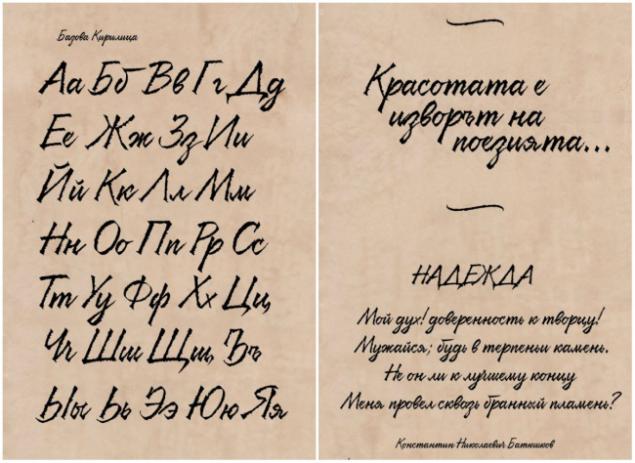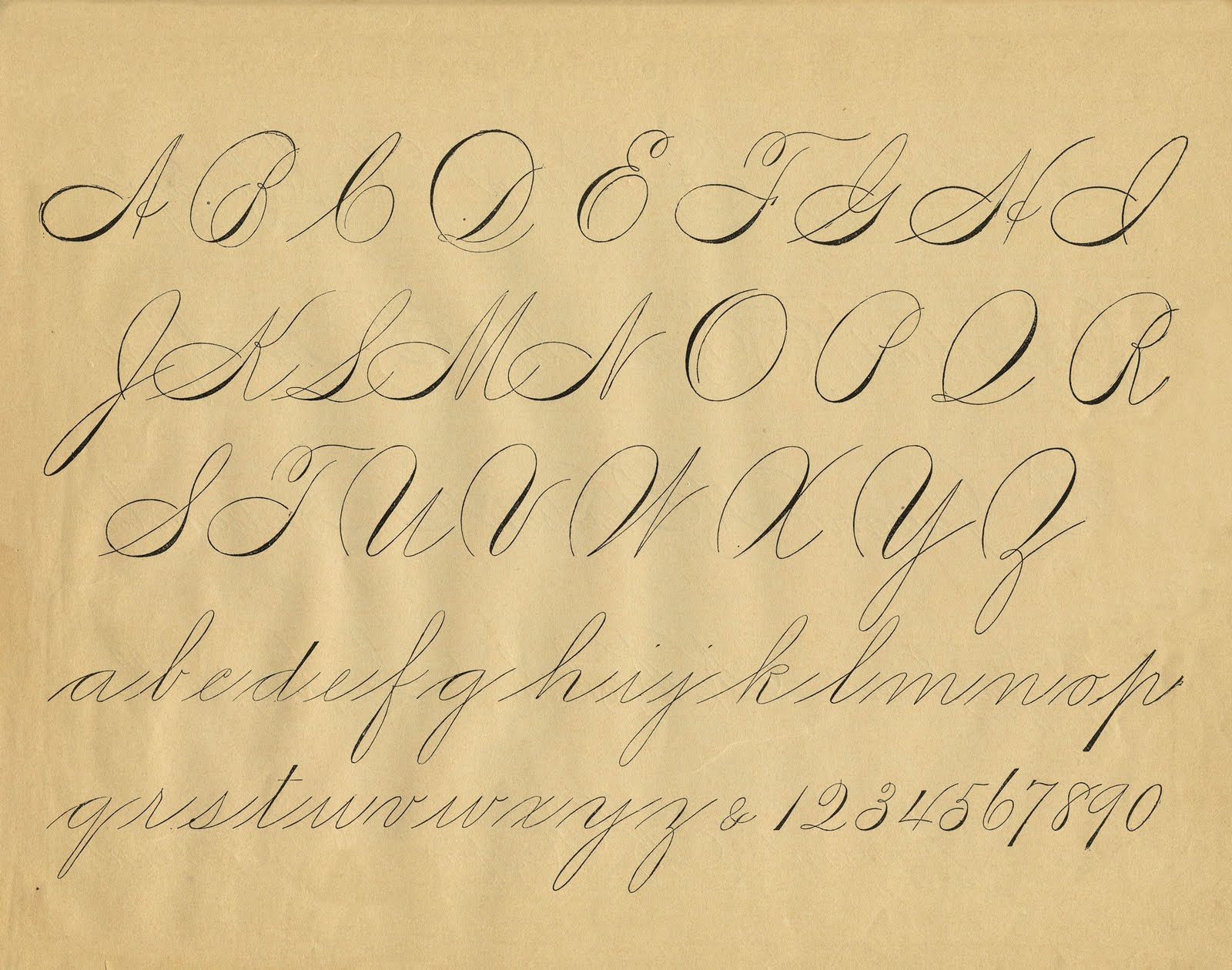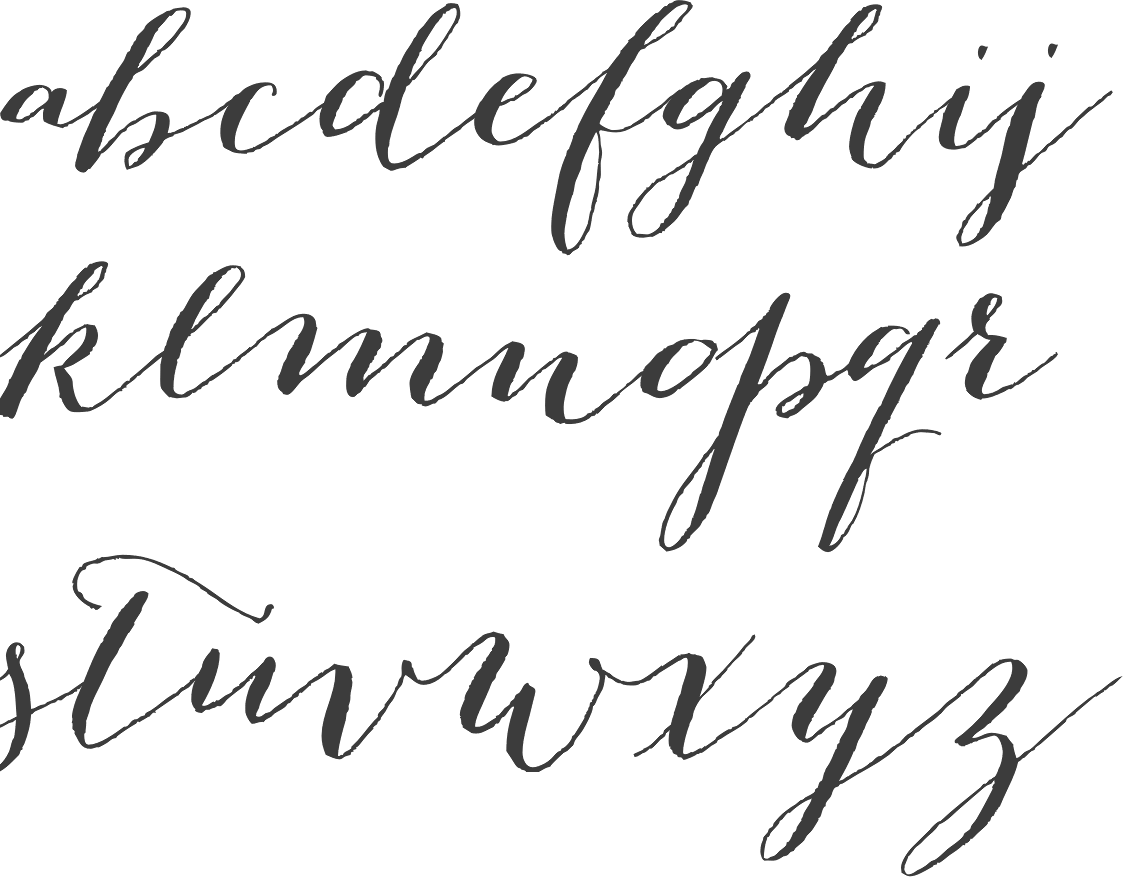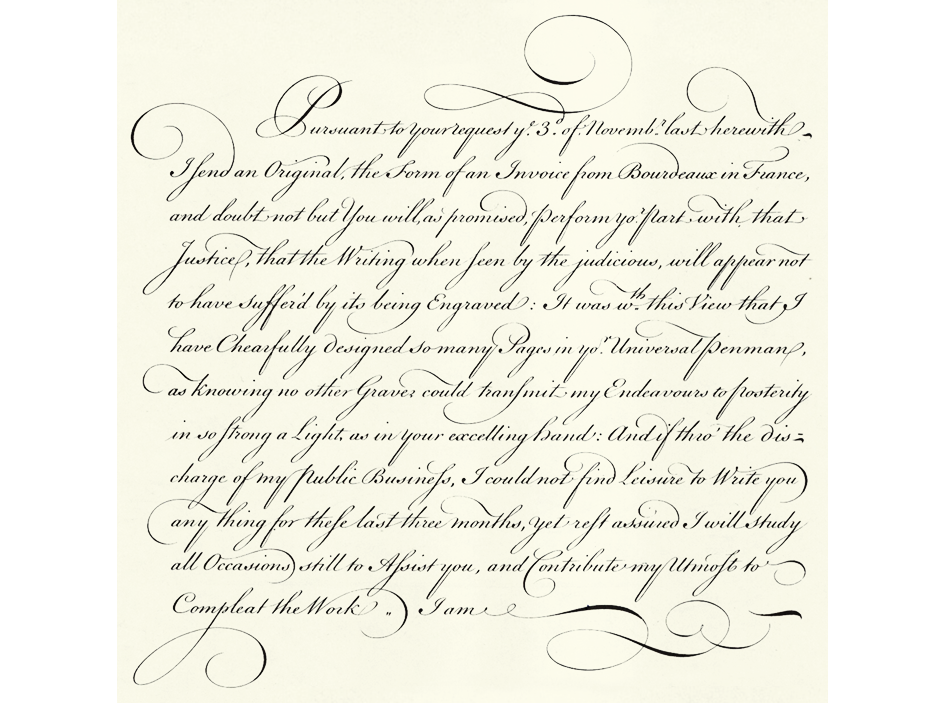
Психология восприятия шрифтов в маркетинге
Влияние шрифта на эмоциональное восприятие в интернет-маркетинге
Психологи выделяют несколько следующих типов шрифтов по их влиянию на настроение потребителей.
Прямые вытянутые шрифты
Сообщают деловое настроение и являются практически универсальными шрифтами. Тем не менее, следует учитывать, что прямой шрифт будет неуместен для немассовой и оригинальной продукции, которую необходимо выделить среди конкурентов. Здесь он может показаться скучным и безликим, если не обыграть его необычным цветовым решением.
Строгие квадратные шрифты
Преимущественно используются в дизайне рекламы промышленных продуктов, технологий и социальной рекламы. Здесь неуместна легкость и простота, эти шрифты призваны настроить человека на серьезность предоставленной информации. Они создают впечатление важности и авторитетности, поэтому рассчитаны на привлечение партнеров по бизнесу и инвесторов.
Округлые шрифты
Передают чувство комфорта и уюта. В то время как квадратные шрифты выглядят суровыми, округлые положительно воспринимаются как доброе отношение бренда к потребителям.
Наклонные шрифты с виньетками
Чаще всего используются для рекламы товаров, у которых целевая аудитория девушки и женщины.
Рукописные шрифты
Не подходят для наружной рекламы так же, как и наклонные шрифты – их сложно читать, если выбран большой размер букв. В то же время, они отлично подходят для того, чтобы подчеркнуть эксклюзивность товара или услуги. Рукописные шрифты используют при рекламе адвокатских и консалтинговых услуг, врачебной практики, для написания пригласительных, при проведении политических пиар-акций. Они вызывают чувство доверия и придают большую достоверность информации.
Стилизованные декоративные шрифты
Шрифты, выглядящие как граффити или готические надписи, стоит использовать только там, где они будут нести соответствующую смысловую нагрузку. Например, совершенно неуместно использовать готический шрифт для рекламы парикмахерской или детского магазина.
Самые популярные шрифты
1. С засечками: Baskerville, Didot, Garamond, Georgia, Times. Ассоциации: традиционный, утонченный, практичный, формальный.
2. Без засечек: Avenir, Futura, Gill Sans, Helvetica, Verdana. Ассоциации: современный, чистый, геометрический, универсальный.
3. Рукописные: Buttermilk, Edwardian, Isabella, Snell Roundhand, Zapfino. Ассоциации: элегантный, классический, утонченный, стильный.
4. Брусковые: Clarendon, Copse, Josefin, Museo, Silverfake. Ассоциации: современный, модный, дружественный, цельный.
Отличие восприятия шрифта с засечками и без них
Шрифты с засечками (serif) читаются легче в печатных работах. Засечки увеличивают контраст между буквами и делают их отличительными. Так нашему мозгу легче распознать букву. Читая шрифт без засечек, мозг тратит больше времени на то, чтобы опознать букву, потому что ее форма не такая отличительная.
Шрифты без засечек (sans serif) лучше использовать для интернета. Также sans serif шрифт хорошо смотрится в наружной рекламе, так как не теряет своих свойств при увеличении. Его часто используют для того, чтобы привлечь внимание. Шрифт без засечек хорошо смотрится и в маленьком размере, но для основного текста лучше использовать с засечками – он не вызывает быстрой усталости.
40% заголовков интернет-изданий написаны с использованием шрифтов с засечками. 66% сайтов используют шрифт без засечек для основного текста.
Существует мнение, что примером удачно выбранного шрифта является такой шрифт, на который читатель не обращает внимания.
Восприятие шрифта в составе логотипа
Всего 6% интернациональных брендов используют в качестве логотипа картинку. 56% используют комбинацию текста и изображения, а логотипы оставшихся 37% брендов – это надписи. Таким образом, подавляющее большинство компаний используют текст при создании логотипа. Нельзя пренебрегать значением шрифта и необходимо уделять достаточно времени созданию логотипа с таким шрифтом, который будет лучше всего сообщать человеку философию бренда.
Логотип, где текст помещен в квадрат или круг, ассоциируется с уверенностью, в эллипсе – с творческим подходом. Перевернутый треугольник выглядит как призыв к действию, а диагональное расположение текста ассоциируется со скоростью и стремительностью.
Лучший шрифт для восприятия
63% используемых шрифтов в логотипах компаний – без засечек. Самый популярный среди них – Helvetica. Этот шрифт используется в 21% лого-надписей. Среди них такие крупные компании как Saint Laurent, Comme des Garsons, HBA, colette.
Helvetica считается лучшим шрифтом для восприятия. Мы тоже «примерили» его к нашему логотипу.
О чем стоит помнить при выборе шрифта: несколько рекомендаций
Для наружной рекламы подходят жирные крупные шрифты, которые легко читаются и контрастируют с фоном. Если рекламу будут читать с расстояния 5 метров, то буквы должны быть не менее 5 см в высоту.
В одном рекламном сообщении не стоит использовать более трех разных шрифтов.
Для общей целевой аудитории идеальный размер кегля – 11-12 пунктов. Если целевая аудитория люди 60+ лет, им больше подойдет шрифт 18 кегля и больше. Для рекламного заголовка лучше использовать кегль от 14 до 30.
Важную роль играет тот факт, что человек читает не отдельные буквы, а группы букв или все слово целиком. Поэтому шрифты с засечками легче читаются в печатных рекламных материалах – буквы выглядят более раздельно.
Разная длина строк может ускорять или замедлять чтение. Необходимо обращать внимание не только на тип шрифта, но и на расстояние между буквами, строчками и т.д.
Ссылки по теме: Создания и продвижения сайта
Выбираем шрифт для логотипа
Как выбрать шрифт и сделать логотип самому?
Одним из ключевых компонентов хорошего (и даже плохого) логотипа является Его Величество Шрифт.
Выбирать шрифт необходимо, придерживаясь если не правил, то, как минимум, принципов. Но для того, чтобы не «увязнуть» в профессиональной терминологии, необходимо познать ее хотя бы отчасти. Только так Вам откроется ответ на вопрос – как сделать логотип самому?
Какими же бывают эти «заветные буковки»?
Есть шрифты, которые имеют так называемые «засечки»
В плеяде профессиональных дизайнеров «бытует поверье», что «засеченный» шрифт помогает держать внимание на строке. Ключевой характеристикой такого шрифта является переход от более толстых линий к тонким.
Как, например, здесь:
Без засечек — Sans Serif
Словно в противовес им созданы шрифты, не имеющие засечек, что, тем не менее, придает им свою привлекательность. Взгляните на эту эстетику прямых углов, четких, ровных линий. Она имеет право на существование!
Где сгодится такой шрифт? Везде! Большинство мировых брендов используют в логотипе шрифт без засечек. Он не заменим там, где требуется подчеркнуть и поставить во главу угла элемент делового стиля.
Рукописные шрифты
А что же рукописные шрифты? Здесь всё сложно. С одной стороны они могут педалировать особую «человечность» бренда, с другой – именно рукописный шрифт, порой, заявляет изящество, роскошь. Вот вам пример – Cadillac.
Разве не похоже это на стильную роспись миллионера, которому совершенно не важно, будет ли прочитана его фамилия или нет?
Архаичный шрифт
Приходилось ли Вам замечать, что мы живем в удивительное время – когда во времени настоящем, сегодняшнего – самый минимум. Нам показывают сериалы о советских временах. В тренде герои вчерашних лет. Заглянем в ГУМ! Нас накормят советским мороженым. Мы можем выпить чаю в советских буфетах, с отнюдь не советскими, разумеется, ценами.
Архаичный шрифт сбитой машинки в логотипе? Почему бы нет, если Вы хотите подчеркнуть, что работаете в отрасли со времен царя Гороха? Смотрится вполне читабельно.
Декоративный шрифт
И, наконец, декоративный шрифт, с его поистине неисчерпаемыми возможностями.
Вариаций декоративных шрифтов миллионы. И оттенков производимого на потенциального потребителя впечатления ничуть не меньше. С помощью логотипа с таким шрифтом, при правильном подходе, можно легко выделиться среди конкурентов. Что Вы хотели бы видеть в логотипе? «Веселуху» или романтичность? Торжественность или щепотку пафоса? Историческую составляющую или агрессивный hi-tech?
Практически каждый день появляется новый интересный шрифт. Но радует пользователей он недолго, так как надоедает всем еще быстрее, чем популярная мелодия, установленная на телефон.
Так как же выбрать нужный шрифт?
Если Вы воспользуетесь представленным на нашем сайте генератором логотипов, то Вам вовсе не нужно ломать голову над этим вопросом. Какой бы знак не был выбран, к нему уже подобран оптимальный шрифт. Но всё же существуют несколько общих правил, о которых стоит рассказать:
- Шрифт обязательно должен отвечать направлению бизнеса.
Представьте себе банк с веселенькими «диснеевскими шрифтами». Возникнет ли доверие у потенциального клиента? Нет. Он испугается, что его могут «весело прокатить» на «финансовой карусели». А теперь вообразите надпись «Детские аттракционы», которая имеет лого а-ля Linked In? Проще всего выбрать «вкусный» шрифт для бизнеса, сходив к конкурентам или открыв их сайты, чтобы посмотреть, какие шрифты являются популярными в избранной Вами сфере бизнеса.
- Читабельность шрифта должна быть по умолчанию безупречной. Уменьшите Ваш логотип до минимума. Хорошо ли при этом читается шрифт? Если да, Вы сделали правильный выбор.
- Напишите несколько строк обычного текста. Проверьте четкость шрифта «на глаз». Не сливаются ли буквы? Что происходит при сжатии? Он смотрится и читается хорошо? Мы Вас поздравляем.
- Как согласуется шрифт с другими элементами логотипа? Часто можно наблюдать распространенную картинку: изящная иконка и массивный, никак не согласующийся с нею шрифт.
Такой логотип может вызвать лишь ироничное отношение.
- Вы нашли не один, а несколько хороших шрифтов? Мы рады за Вас. Но не стоит использовать в логотипе больше одного. В крайнем случае будут уместны два шрифта. Но, все же, по нынешним меркам это много.
- Насколько типичен Ваш шрифт? Представляет ли он собой клише? Если Вы используете Comic Sans для того, чтобы сделать надпись на логотипе, который будет принадлежать компании, занимающейся развлечениями и юмором, это не очень правильно.
- Не стоит превращать подбор шрифта для логотипа в фанатичную «погоню за трендом». Не обязательно использовать шрифт, появившийся вчера или находящийся на пике популярности. Всё новое рано или поздно становится старым.
Нет времени заниматься подбором шрифтов? Попробуйте подобрать логотип онлайн на нашем сайте, где разработан уникальный генератор логотипов.
Мы искренне желаем Вам удачи!
30 классных бесплатных шрифтов на 2019 год
1.
Для личного и коммерческого использования. Много дополнительных символов, 18 начертаний и кейс на беханс — тут.
2. The Circus Display
Винтажный шрифт, доступный за подписку тут.
3. Arkipelago
Бесплатный для личного и коммерческого использования, доступен здесь.
4.Tradesmith
Винтажный индустриальный шрифт, для личного и коммерческого использования, доступен тут за подписку.
5. Colus
Акцидентный шрифт — и кириллица есть. Ищите тут.
6. Colortube
Говорят, первый цветной шрифт. Нужен Adobe CC 2018, чтобы правильно всё работало. Пока кириллицы нет, но планируют добавить. Скачать можно здесь.
7. Briberra
Доступен за подписку, есть возможность добавлять подчёркивание. Скачать тут.
8. Aloja
Базовый набор бесплатно здесь, расширенный — за пять баксов. Для личного и коммерческого пользования.
9. Cunia
Просто приятный акцидентный шрифт, достаточно плотный, чтобы сделать по-настоящему жирно — для личного и коммерческого использования. Как и многие другие — за подписку здесь.
10. Space Grotesk
Вариация Space Mono, скачать можно здесь.
11. Horizon
Тонкий рукописный шрифт — ищите по ссылке.
12. Buckwheat
Целых три шрифта, несколько языков, с текстурами и всеми делами — здесь. Есть OTF и SVG, который работает в Photoshop CC 2017 и Illustrator CC 2018 или новее.
13. Free Fat Font!
«Бесплатный жирный шрифт» — много дополнительных символов, доступен по подписке.
14. Understock
Винтажный шрифт с тремя стилями — здесь.
15. Finland
Бесплатно OTF и TTF найдёте тут, а полную шрифтовую семью можно скачать за 15 баксов.
16.
По ссылке SVG, для которого нужны Photoshop CC 2017 или Illustrator CC 2018 (и новее), и TTF, который выглядит уже не так круто.
17. Serico
Всё для вашего личного и коммерческого использования — здесь.
18. Bobby Jones
Раздолбайский акцидентный црифт для личного использования — в бесплатной версии три стиля.
19. Puzzled
Рукописный шрифт для личного и коммерческого использования доступен по подписке здесь.
20. Anodina
Симметричный с пятью начертаниями — найдёте здесь.
21. Object Sans
Рабочая лошадка с кириллицей. Кейс и ссылку на скачивание найдёте на беханс.
22. Bripokus Stencil Font
Конденсный акцедентный шрифт — для личного и коммерческого использования тут.
23. Hansief
Винтажный шрифт — ждёт, пока вы его скачаете, тут.
24.
Ещё один рукописный красавчик с возможностью использовать экстрабольшие заглавные буквы — например, для подписей. Доступен по подписке здесь.
25. Mindfully
Рукописный шрифт с четырьмя начертаниями ждёт вас по ссылке.
26. Rustico
Рукописный all caps — найдёте здесь.
27. Aileron
Бесплатно или за донат 16 стилей для личного или коммерческого использования ждут вас здесь.
28. Big John/Slim Joe
Вот тут, свободный для личного и коммерческого использования.
29. Disclaimer
Шикарный. Конденсный. Акцедентный. 2 стиля. Здесь.
30. Fixer
7 шрифтов — обычные, обводочные и 3D — по ссылке.
Здесь Вы найдете кириллические шрифты для photoshop, word и других программ. | |||||||||||||||||||||||||||||||||||||||||||||||||||||||||||||
| |||||||||||||||||||||||||||||||||||||||||||||||||||||||||||||
Страница 1 из 10 |
%d0%ba%d1%80%d0%b0%d1%81%d0%b8%d0%b2%d1%8b%d0%b9 %d1%88%d1%80%d0%b8%d1%84%d1%82 %d0%b4%d0%b5%d1%82%d1%81%d0%ba%d0%b8%d0%b9 пнг образ | Векторы и PSD-файлы
Мемфис дизайн геометрические фигуры узоры мода 80 90 х годов
4167*4167
аудиокассета изолированные вектор старая музыка ретро плеер ретро музыка аудиокассета 80 х пустой микс
5000*5000
бумбокс с разноцветными музыкальными нотами
1200*1200
Мемфис шаблон 80 х 90 х годов стилей фона векторные иллюстрации
4167*4167
я выбираю быть геймером потому что в реальной жизни ничего эпического не происходит
1200*1200
аудио кассета плоский дизайн
1200*1200
80 основных форм силуэта
5000*5000
flamingo летние вибрации векторные иллюстрации
5000*5000
Сделано в 1989 году ограниченным тиражом типография премиум футболка дизайн вектор
5000*5000
значок кассеты мультяшном стиле
5000*5000
все радужные цвета морщинистый фольги
1200*1200
дизайн плаката премьера фильма кино с белым вектором экрана ба
1200*1200
ретро восьмидесятых бумбокс
1200*1200
все радужные цвета морщинистый фольги
1200*1200
shiba inu собака ретро векторные иллюстрации
5000*5000
лейбл онлайн трансляций с ярко синими розовыми неоновыми цветами и современным дизайном
1200*1200
лев крутые ретро очки векторная иллюстрация король лев
5000*5000
непрерывный рисунок линии старый радио музыка знак винтажный вектор одна линия искусство простота иллюстрация минималистичный дизайн
4667*4667
Мемфис круги рисованной круглые формы геометрические гранж дизайн в горошек орнамент изолированные декоративные объекты
5000*5000
кошка ретро красочные иллюстрации
5000*5000
набор векторных продаж этикетки
800*800
игра над типографикой дизайн футболки
4000*4000
Мемфис 90 х годов мода бесшовные модели
4167*4167
кассетаОдна непрерывная линия рисования музыкальный инструмент
4667*4667
Скидка 80 процентов на 3d золото
3000*3000
мопс голова собаки красочные векторная иллюстрация
5000*5000
голова льва ретро очки векторная иллюстрация король лев
5000*5000
набор векторных продаж этикетки
800*800
Мемфис шаблон 80 х 90 х годов на белом фоне векторная иллюстрация
4167*4167
ретро радуга сердце
1200*1200
нло принять закат ретро иллюстрация
5000*5000
мопс собака моды векторные иллюстрации
5000*5000
йети и гепард закат ретро вектор иллюстрация
5000*5000
мемфис бесшовной схеме 80s 90 все стили
4167*4167
Акула серфинг закат векторные иллюстрации
5000*5000
yeti играет на сноуборд векторные иллюстрации
5000*5000
радуга кататься на роликах
1200*1200
Буква c с логотипом дизайн вдохновение изолированные на белом ба
1200*1200
инопланетные наклейки векторные иллюстрации
5000*5000
горилла наушники с иллюстрацией ретро
5000*5000
holographic iridescent color wrinkled foil
1200*1200
Кокосовый череп ретро векторные иллюстрации
5000*5000
у меня есть герой я зову его папа дизайн футболки
2100*2100
3д 80
3000*3000
3d рекламная скидка 80 золота с сердцем
2000*2000
набор векторных иконок реалистичные погоды изолированных на прозрачной ба
800*800
Рамка потоковое наложение
3500*3500
панда скейтборд закат ретро векторная иллюстрация
5000*5000
3d номер 80 люкс
5000*5000
магазин сейчас большая распродажа до 80
1200*1200
Открытка с рукописным шрифтом | Детский художник
Как приятно получать поздравления! Как приятно поздравлять!
Поздравительная открытка ручной работы – один из самых простых и в то же время изящных способов сделать приятно любимому, уважаемому, дорогому человеку.
В старину открытки появились как открытый вид письма — карточки с открытым текстом. После их стали украшать различными изображениями. Первая иллюстрированная открытка была напечатана во Франции.
Сейчас открытка, сделанная специально для человека, для мероприятия (пригласительная открытка на свадьбу) стала очень популярной, и получить её в подарок — всегда приятно!
Я считаю, что лучшая открытка – это открытка ручной работы, сделанная индивидуально для конкретного человека, учитывая его чувства, характер и интересы, потому, что самый дорогой подарок – это внимание и уважение.
В этом случае – авторская рукописная открытка – подходит более всего. Нарисованная профессиональным художником иллюстрация, с текстом, написанным от руки каллиграфическим почерком (шрифтом) придаёт простому подарку безупречную элегантность и изысканность. Такой подарок без сомнения дарить и получать очень приятно!
Именно каллиграфический шрифт передаст всю восторженность события, всю радость приближающегося праздника. Самим выбором шрифта, написанием букв уже можно угадать характер самого человека. Уже буквами — раскрыть образ нежной девушки, чопорной дамы, веселого юноши.
Красиво сочетать каллиграфические буквы с изображением, выстроить композицию меня учила моя лучшая преподавательница — Елена Анатольевна Дербилова. Эта потрясающая женщина вместила в себя и музыку (играла на скрипке), и танец (балет), и изобразительное искусство. Но по её мнению — рукописный шрифт вбирает все эти три понятия — он создаёт новую музыку, буквы — застывают танце…
Каждый раз, когда меня просят сделать открытку — я подхожу ответственно.
Данные примеры двух открыток — адресованы девушке. Поэтому они нежны и поэтичны, как сама получательница, а рукописным шрифтом я хотела передать её непоседливый характер.
По-моему – получилось.
- Рукописная открытка
Заказать стильные открытки Вы можете здесь.
Поделиться в соц. сетях
Следующая запись
С Днем Учителя!С лучами радостного солнца октября пришел долгожданный многими праздник – День учителя. Я думаю, ребята, у…
Детский рукописный шрифт | Бесплатное письмо для детей
Загрузить- Темный режим
- Помощь Войти
- Шрифты
- Стили
- Коллекции
- Генератор шрифтов
- (͡ ° ͜ʖ ͡ °)
- Дизайнеры
- Материал
Связанные стили
Cool
Fancy
Script
Cute
Рукописный ввод
Bold
Fun
Kids
Наброски
Мультфильм
Рисованный
Фанки
Праздник
Тонкий
Вечеринка
Ручной работы
Художественный
- 9004 Сладкий
- 9004
Дети
Школа
Причудливый
Девчачий
Дисплей
Игривый
Класс
Дудлы
Crazy
Интересно
Primary
Wild
Child
Silly
Lines
Print Writing
Маркер
2 9250004 9250004
Сортировать по
- Популярные
- В тренде
- Новейший
- Имя
Для личного пользования Бесплатно
289.
7k загрузок
Для личного пользования Бесплатно
144.7k загрузок
Для личного пользования Бесплатно
128,5k загрузок
Для личного пользования Бесплатно
359,5k загрузок
Для личного пользования Бесплатно
14451 загрузок
100% бесплатно
53727 загрузок
Для личного пользования Бесплатно
Обычные2744 загрузки
Для личного пользования Бесплатно
39117 загрузок
100% бесплатно
8392 загрузки
Для личного пользования Бесплатно
15628 загрузок
Для личного пользования Бесплатно
233.4k загрузок
Для личного пользования Бесплатно
218.7k загрузок
Для личного пользования Бесплатно
Обычный4488 загрузок
Для личного пользования Бесплатно
4940 загрузок
Для личного пользования Бесплатно
19202 скачиваний
От 1 до 15 из 311 Результаты
- 1
- 2
- 3
- 4
- Далее
Еще больше стилей
- Популярные шрифты
- Коммерческие шрифты
- Классные шрифты
- Курсивные шрифты
- Блог
- Справка
- Контакты
- Бренд
- Конфиденциальность
- Условия
- DMCA 9000pace4
- Карта сайта
- 401 Бесплатные дети, рукописные шрифты — FontSpace
Мгновенная загрузка для 401 бесплатного ребенка, рукописные шрифты. Для вас, профессионалов, 35 на 100% бесплатны для коммерческого использования!
- 25 бесплатных детей, Рукописные шрифты · 1001 шрифт
У нас есть 25 бесплатных детских рукописных шрифтов, которые мы можем предложить для прямой загрузки · 1001 Fonts — ваш любимый сайт бесплатных шрифтов с 2001 года.
- 7 бесплатных детских шрифтов, рукописный ввод, детские шрифты · 1001 шрифт
У нас есть 7 бесплатных детских, рукописных и детских шрифтов, которые мы можем предложить для прямой загрузки · 1001 Fonts — ваш любимый сайт бесплатных шрифтов с 2001 года.
- 401 Бесплатные дети, рукописные шрифты (Страница 2) — FontSpace
Мгновенная загрузка для 401 бесплатного ребенка, рукописные шрифты.
Для вас, профессионалов, 35 на 100% бесплатны для коммерческого использования! (Стр. 2)
- Рукописные шрифты — Страница 3-1001 Бесплатные шрифты
Рукописные шрифты — Страница 3. 1001 Free Fonts предлагает огромный выбор бесплатных шрифтов. Загрузите бесплатные шрифты для Windows и Macintosh.
- Рукописные шрифты — Страница 1-1001 Бесплатные шрифты
Handwriting Fonts — Страница 1. 1001 Free Fonts предлагает огромный выбор бесплатных шрифтов.Загрузите бесплатные шрифты для Windows и Macintosh.
- 50 отличных бесплатных рукописных шрифтов | Creative Bloq
50 отличных бесплатных рукописных шрифтов. Составлено сотрудниками Creative Bloq. ОБНОВЛЕНИЕ типографики. Рукописные шрифты сейчас популярны как никогда — вот 50, которыми вы можете владеть бесплатно.
- Скачать бесплатные детские шрифты — Cool Text
Kids Fonts Самые популярные … Laban — dustBUSt Fonts — Kids Скачать шрифт Laban (17,199 загрузок).
.. Рукописный ввод, трудный для чтения, ужас, огромный международный детский
Самые популярные шрифты
Родственные и похожие шрифты
- Quicksand Dash — красивый, четкий печатный шрифт, который представлен в различных стилях, включая версию с пунктиром .
- KG Primary Dots — точечный принт в четырех стилях — простые буквы и три разных варианта с линией.
- KG Primary Penmanship — этот четкий рукописный шрифт доступен в нескольких стилях, включая отображение в пунктирных третьих строках как показано выше.
- Berner Basisschrift — этот рукописный шрифт представлен в двух стилях — печатном и прекурсивном с маленькими крючками на буквах, как показано выше.
- правильное формирование букв
- единый размер письма
- униформа наклонная
- шаг
- KG Пустое пространство Solid — хороший, четкий печатный шрифт, отлично подходит для детей, чтобы писать на нем или коллажи.
- Quicksand — красивый, четкий печатный шрифт, который представлен в различных стилях, включая полужирный и пунктирную версию, показанную выше. (C)
- Arcon — чистый и простой шрифт, который легко читать и отлично подходит для написания историй. (C)
- KG Primary Penmanship — этот четкий рукописный шрифт имеет несколько стилей, включая отображение в пунктирных третьих строках, как показано выше.
- Berner Basisschrift — этот рукописный шрифт представлен в двух стилях — печатном и прекурсивном с маленькими крючками на буквах, как показано выше.
- Четкая печать — четкий печатный шрифт со сплошными и пунктирными вариантами. (C)
- Abeezee — аккуратные, легко читаемые печатные буквы. (C)
- KG Primary Dots — пунктирная печать в четырех стилях — простые буквы и три разных варианта с линией.
- KG Red Hands Outline — контурный шрифт, который идеально подходит для обводки или раскрашивания.
- Victorian Modern Cursive — это стиль почерка, которому моих детей учат в школе — хотя стиль преподаваемого почерка действительно варьируется от штата к штату здесь, в Австралии, это четкий шрифт с предварительной настройкой.
- 1
26
бесплатных рукописных шрифтов для детей
Лучший веб-сайт с бесплатными высококачественными детскими шрифтами Handwriting Kids, с 30 бесплатными шрифтами Handwriting Kids для немедленной загрузки и 68 профессиональными шрифтами Handwriting Kids по лучшей цене в Интернете.
30 бесплатных рукописных детских шрифтов
Обратите внимание: если вы хотите создать профессиональную распечатку, вам следует подумать о коммерческом шрифте. Бесплатные шрифты часто содержат не все символы и знаки и не содержат пар кернинга (Авеню ↔ Место проведения, Чай ↔ Чай).
Проверьте это бесплатно с Typograph.
Откройте для себя огромную коллекцию шрифтов и графических ресурсов, проверенных вручную.Все необходимые шрифты и многие другие элементы дизайна доступны по ежемесячной подписке, подписавшись на Envato Elements. Подписка стоит 16,50 долларов в месяц и дает неограниченный доступ к огромной и постоянно растущей библиотеке, состоящей из 1500000+ элементов, которые можно загружать сколько угодно часто (в том числе стоковые фотографии)!
Эти 10 детских шрифтов сохранят молодость души
Создать дизайн, ориентированный на детей, может быть сложно.
Если вы слишком сильно будете стараться «быть с детьми», вы просто будете выглядеть глупо.Возможно, лучший способ подойти к дизайну для детей — поговорить с ними на их собственных условиях.
Это мышление, лежащее в основе этих 10 удобных для детей шрифтов, которые варьируются от маленьких детских мелков до забавных пузырьков и аккуратных рукописных текстов, достойных полных оценок на любом школьном тесте по письму. Comic Sans, уходи! Эти детские шрифты идеально подходят для дизайна упаковки, плакатов и книг.
Отличный шрифт с дерзким сообщениемФормат: TT
Начало нашего списка лучших детских шрифтов — это правильно названный Kids Crayon.Этот текстурированный шрифт, выполненный в точности так, как написано на банке, взят из почерка пятилетних детей создателя Яна Уильямса. Со всеми особенностями, которые могут создать только дети, этот очаровательный шрифт обойдется вам всего в 7,99 фунтов стерлингов (около 10 долларов США).
Этот шрифт сочетает каллиграфию с детским письмом.Формат: OTF, TT
Детский текст не всегда неуклюжий и меловой. Возьмем, к примеру, Kids Script, шрифт, основанный на моделях каллиграфического почерка, которые использовались в испанских школах в 1940-х годах.Это может показаться эзотерической отправной точкой, но в результате получился свежий шрифт с уникальными краями. Загрузите семейство из трех шрифтов за 49,99 фунтов стерлингов (около 63,50 долларов США).
Эта серия возникла при разработке приглашений на день рождения.Формат: OTF
PF Kids Pro — еще один шрифт, который использует реальный текст в качестве отправной точки. В этом случае дочь Александроса Папалексиса может найти свое письмо, увековеченное в форме шрифта. Этот грубый шрифт, созданный при оформлении приглашений на ее день рождения, доступен в трех версиях по цене 140 фунтов стерлингов (около 177 долларов США).50).
Этот причудливый шрифт имеет множество привлекающих внимание уловок.Формат: OTF
Время для чего-то совершенно другого. Разговаривать с детьми их собственным почерком — это хорошо (и это еще не все), но иногда шрифт должен привлечь их внимание. Откройте для себя La Mona Kids, забавный пузырьковый шрифт, наполненный странными деталями, которые невозможно игнорировать. Более того, вы можете получить восемь шрифтов из этого семейства всего за 35,99 фунтов стерлингов (около 45 долларов.50).
Мы не уверены, что это лучший слоган для детского шрифта.Формат: OTF
Перейдите на страницу загрузки Butterfly Kids, и вы увидите, что шрифт описывает себя как «распространяющийся» развеселись! Будь милым. Будь счастлив! » С его фигурными буквами и лигатурами OpenType нам трудно не согласиться. Этот единственный шрифт вы можете скачать всего за 13,99 фунтов стерлингов (около 18 долларов США).
Красота мела на классной доске без ужасного шумаФормат: TTF
Другой шрифт из школьного лагеря, Cool Crayon — это шрифт, имитирующий песчаную текстуру мела на классной доске.
Мы все сидели рядом с кем-то в классе, кто расставил точки над i сердечками(Хотя мы не можем не думать, знают ли дети в наши дни, что такое классные доски? Ответы на открытке … или, может быть, в твите.) Этот шрифт доступен бесплатно только для личного использования, но вы можете лицензировать его у дизайнера. Сайт Дэвида Керкхоффа Hanoded Fonts.
Формат: TTF
Может быть, это только мы, но этот шрифт — типографское воспоминание о том, что мы сидим рядом с кем-то в школе, кто расставил точки над i с любовью сердца и, скорее всего, писали неоновой гелевой ручкой.В любом случае Cookie Monster — это забавный детский рукописный шрифт, который вы можете бесплатно скачать для личного использования (или обсудить коммерческую лицензию с дизайнером Десом, используя контактные данные в описании шрифта).
(по-французски это безумие карандашей)Формат: TT
Если ни один из других карандашных шрифтов в нашем списке не совсем то, что вы ищете, возможно, Crayon En Folie — это то, что вам нужно.
Это не, не повторяем, Comic SansЭтот детский шрифт берет ваш стандартный карандашный шрифт и дает им всплеск цвета.Загрузите его за 10,99 фунтов стерлингов (около 14 долларов США).
Формат: OTF
Симпатичный шрифт с Sans в названии? Не волнуйтесь, у JollyGood Sans нет тошнотворного края Comic Sans. Фактически, этот шрифт приятен для глаз и стал более тонким, поэтому на странице можно разместить больше букв. И учитывая, что он предназначен для плакатов и книг, это тоже практичный выбор дизайна. Загрузите восемь шрифтов за 70,99 фунтов стерлингов (около 90 долларов США).
Детский шрифт с окончательным названиемФормат: TTF
Когда детский шрифт называется просто Kids, вы знаете, что вы на пути к победителю.Вспоминая чернильные буквы, которые вы найдете в тетрадях (опять же, они все еще актуальны? Или это все iPad сейчас в классах?), Этот набор поставляется с прописными и строчными буквами, а также целым рядом цифр и символов.
Лучше всего то, что вы можете получить его бесплатно.
Прочтите некоторые из наших замечательных постов, например:
Move over Comic Sans — лучшие шрифты для учащихся и начинающих писателей
Comic Sans: закругленный шрифт без засечек с одноэтажной буквой «а» и упрощенной буквой «g» часто выбирают учителя, ищущие для создания учебных и учебных материалов.
Конечно, визуально дизайнеры склонны внутренне стонать, когда видят, что используется экземпляр Comic Sans; возможно, дело в том, что его «привыкли к смерти», может, он просто не так привлекателен визуально или, как объясняют некоторые дизайнеры шрифтов, слишком часто и слишком долго использовался ненадлежащим образом. В любом случае, Comic Sans подвергается серьезным издевательствам, на самом деле существует даже движение «запретить Comic Sans».
Имея это в виду, мы рассмотрели широкий спектр типов шрифтов, свободно доступных из шрифтов Google, и нашли несколько вариантов, которые идеально подходят для начинающих писателей (как печатные, так и скорописные), а также некоторые шрифты, основанные на рукописном письме.
Мы перечисляем наши любимые бесплатные шрифты от Google следующим образом:
Лучшие курсивные шрифты от Google
Вот 7 лучших курсивных шрифтов от Google. Более известные как скриптовые шрифты, буквы в этих шрифтах заставляют слово выглядеть связанным, как если бы вы писали курсивом. С технической точки зрения, это связанный или полусвязанный шрифт, вдохновленный рукописными буквами, кистью или каллиграфией. Некоторые курсивные шрифты более формальные, а другие склоняются к непринужденным и игривым.Обратите внимание, что все курсивные шрифты, представленные ниже, имеют одноэтажные глифы «а».
Allura — полуформальный курсивный шрифт Cookie — формальный курсивный шрифт, основанный на каллиграфии кисти Montez — формальный курсивный шрифт Sacramento — случайный курсивный шрифт с использованием точных точек 7 БЕСПЛАТНЫХ курсивных шрифтов, которые можно использовать с маленькими учениками. Click To TweetЛучшие пунктирные шрифты от Google
Пунктирные шрифты идеально подходят для детей, которые учатся писать.
Raleway Dot — строчные и прописные буквы, но двухъярусная «а» Учишься писать? Эти шрифты отлично подходят для создания рабочих листов для начинающих писателей. Click To TweetЭти шрифты вдохновлены рекламными щитами, знаками и огнями. Вы можете использовать его для заголовков, плакатов и рабочих тетрадей, а также для больших заголовков.Хотя у Google ограниченная коллекция шрифтов с точками, ниже вы можете найти другие шрифты с точками.
Пунктирные шрифты из источников, отличных от Google Fonts.
Лучшие рукописные шрифты от Google
Рукописные шрифты предлагают более неформальное и удобное отображение контента. Они отличаются от приведенных выше курсивных кистей или рукописных списков рукописного ввода, поскольку они в основном представляют собой отдельные буквы и носят более случайный и игривый характер.
Handlee — обычный рукописный шрифт Ranga — более жирный наклонный шрифт для большего воздействия Zeyada — рукописный шрифт с завитками и кривыми, почти курсивными Упростите задачу для молодых учащихся с помощью дружелюбного рукописного текста с помощью этих бесплатных шрифтов Click To TweetОбратите внимание, что все шрифты ниже имеют одноэтажные глифы «а».
Рукописные шрифты из других источников, кроме Google:
Лучшие шрифты для печати, удобные для детей от Google
Эти шрифты отлично подходят для детских сборников рассказов, рабочих тетрадей, плакатов и листовок. Они нравятся малышам, поскольку они просты и удобны с определенной формой, чтобы помочь тем, кто учится читать и писать.
ABeeZee — детский шрифт для обучения, , Andika — разработан для использования с грамотностью , , с учетом потребностей начинающих читателей, Amaranth — , удобный курсивный шрифт Caudex — предназначен для печати старого рукописного текста — округлый геометрический шрифт без засечек Fredoka One — забавный полужирный, округлый и крупный шрифт для заголовков и крупный шрифт. Выделение — профессиональный вид, но дружелюбный. легкий небрежный вид и круглые чаши.Идея состоит в том, что формы букв понятны и их нелегко спутать друг с другом.Шрифты, специально разработанные для обучения, выделены ниже:
Poppins — геометрический шрифт без засечек
Questrial — современный, читаемый, полный круговой шрифт Quicksand — без засечек с закругленными концами strokeViga — жирный и квадратный Эти бесплатные шрифты Google, предназначенные для написания рассказов для детей, предназначены для повышения грамотности и обучения. Click To TweetРукописный ввод — Обучение курсиву и рукописному письму
Рукописный ввод для детей и взрослых.
Свободный скорописный почерк и рукопись рабочие листы и шрифты , полезные для практики детей домашнего школьного образования или обучение д’нейскому алфавиту и другим стилям письма . На странице ниже представлены отличные ресурсы для улучшения скорописного письма и обучения аккуратной печати как для взрослых, так и для детей.
Об обучении почерку
Шрифты — стили письма
История почерка
Левши
Проблемы и решения
Программное обеспечение для обучения письму
Рабочие листы для улучшения почеркаОб обучении почерку
Бесплатная распечатка рабочих листов для рукописного ввода
Как улучшить навыки почерка у детей
Навыки почерка — важная развивающая задача и занятие для детей.С помощью почерка они могут выражать себя и общаться с окружающим миром. Улучшение их почерка, разборчивости, понимания карандашей и работа над проблемными областями — все это важные вещи, на которые необходимо обратить внимание, будь то родитель на домашнем обучении, учитель, терапевт или просто дополнение к занятиям вашего ребенка в классе.Как научить писать от руки
Наблюдайте за практикой, чтобы дети не заполняли страницу неподходящей работой, просто чтобы быстро закончить. Хвалите буквы и слова, написанные хорошо, и попросите ученика стереть и переписать все неприемлемое.Хотя это может показаться трудоемким, помните, что на самом деле потребуется больше времени, чтобы избавиться от вредных привычек. Почерк состоит из четырех компонентов, независимо от того, учится ли ребенок печатать буквы или писать курсивом, «соединенным»:Шрифты — стили написания
Dyslexie
Шрифт, который поможет тем, кто склонен переворачивать буквы, просто не может различать буквы по какой-либо причине.Хотя этот шрифт не предназначен для рукописного ввода, вы можете распечатать рабочие листы этим шрифтом, чтобы помочь ребенку с дислексией.Educational Fontware, Inc.
EFI производит и продает стиль D’Nealian®, стиль Zaner-Bloser ©, стиль рукописного ввода без слез (TM), стиль Harcourt Brace®, стиль Peterson Directed Handwriting ©, стиль McDougal, Littell Рукописные шрифты в стиле ©, Getty-Dubay Italic (TM), SSD и Palmer. Коммерческий сайт.Jardotty
Шрифт Windows True Type (.ttf), который можно загрузить прямо по этой ссылке.Джардотти — это алфавит с точками, который подходит для создания ваших собственных отслеживаемых листов рукописного ввода. Создано Кристофером Джарманом. (Восстановленная версия для Windows XP — Спасибо, Джефф Велч!)Jarmon
Шрифт Windows True Type (.ttf), который можно загрузить прямо с этого веб-сайта. Курсивный рукописный шрифт Christopher Jarman. Версия Жардотти, сплошная линия.Kids Fonts — помощь в написании текста для школьников на дому.
Неважно, занимаетесь ли вы домашним обучением или просто устали от заранее подготовленных рабочих листов, доступных педагогам дошкольного образования, Kids Fonts здесь, чтобы помочь! Помощь по написанию текста для домашних школьников.Learning Curve BV / Learning Curve BV Пунктирная
Learning Curve BV содержит две версии: одна простая, а другая пунктирная. Этот шрифт также содержит набор дингбатов, которые помогают отрабатывать элементы скорописи.Четкая печать
Сплошная штриховая линия. Из Blue Vinyl Fonts, в котором есть много хороших бесплатных шрифтов для письма и других целей.Школьные шрифты
Mac и Win. Коммерческий. Гарнитуры шрифтов Block Letters и Cursive Handwriting позволяют любому пользователю компьютера создавать упражнения, которые следуют принципам подхода D’Nealian® или Zaner-Bloser® и методам обучения формированию букв.История почерка
Краткая история почерка
«Заимствуя аспекты этрусского алфавита, древние римляне были одними из первых, кто разработал письменный сценарий для транзакций и переписки. ”Левши
Совет: при создании рабочих листов для левшей размещайте образцы сверху, а не слева.
Anything Left-Handed — Вы левша?
Мы — группа левшей, которые предоставляют продукты и информацию, чтобы немного облегчить жизнь левшам во всем мире, и проводят кампании, направленные на повышение осведомленности, принятия и сочувствия к левшам.Уровень аварийности у левшей намного выше, чем у правшей. Знаете ли вы, что наклон влевоDKL Cursive и DKR Cursive
Эти шрифты созданы по образцу методов рукописного ввода из учебника «Навыки написания курсивом» Дайаны Хэнбери Кинг. Г-жа Кинг выпустила как правую, так и левую версию.Проблемы и решения
Адаптации и модификации для учащихся с проблемами почерка и / или дисграфией
Многие учащиеся с трудом создают аккуратные, выразительные письменные работы, независимо от того, есть ли у них сопутствующие физические или когнитивные трудности.Они могут узнать гораздо меньше из задания, потому что они должны сосредоточиться на механике письма, а не на содержании.Дисграфия
Часто дисграфию понимают неправильно.Родители и учителя могут подумать, что вы ленивы или не заботитесь о чистоте. Это означает, что вам нужно еще больше постараться, чтобы показать, что вам не все равно.
Handwriting Club
Использование стратегий сенсорной интеграции для улучшения почерка. У учащихся с проблемами сенсорной обработки, сенсорной осведомленности и / или перцептивных навыков обычно возникают проблемы с почерком.Карман, полный терапии
Продает писчую бумагу и миллиметровую бумагу с выпуклыми линиями, чтобы сенсорные учащиеся могли «чувствовать» свой путь во время письма.Рабочие листы для улучшения почерка
Адресация на конвертах. Практика.
. Распечатайте эти конверты и марки, чтобы использовать их для тренировки правильной адресации и печати на конвертах.The Amazing — Невероятный редактор листов для рукописного ввода
Позволяет вам составить рабочий лист с именем вашего ребенка или коротким предложением любым из 5 шрифтов, рукописным шрифтом или курсивом.Создание рукописного ввода
Создайте свой собственный рабочий лист с помощью этой формы из EdHelper. Поддерживает печать, курсив и д’Налианский.Callirobics
Коммерческий сайт. Упражнения по письму под музыку для улучшения навыков мелких мышц и координации глаз и рук. Подходит для тех, кто учится на слух, от мала до велика.Рабочие листы д’Неалийского алфавита
Изучите и практикуйте рукописный почерк с забавными раскрасками. Они подходят для дошкольных учреждений, детских садов и начальной школы.Бумага для рукописного ввода Донны Янг
Серия PDF-файлов с градуированной линованной бумагой, которые можно использовать в самых разных целях для свободного письма. В некоторых есть место наверху для изображения.Набор доски объявлений Alphabet Line от Jan Brett.
Jan имеет такой очаровательный набор плакатов с алфавитом, что вы захотите, чтобы они украсили вашу комнату. Они представлены в традиционном, скорописном и современном рукописи.Бесплатный лист для рукописного ввода
Рабочие листы для печати от ABC Teach.Практические листы по письму
Эти листы могут быть распечатаны и воспроизведены родителями, опекунами и учителями для использования дома или в классе.Коллекция Донны Янг.Рабочие листы для рукописного ввода
Некоторые довольно простые рабочие листы для начинающих печатников. Один шрифт Zaner Bloser.Рукопись рукописного ввода
Введение в письмо прилагается к книге «Научите ребенка читать за 100 простых уроков» (партнерская ссылка). На сайте Донны Янг.Теги: язык, искусство, письмо
Лучшие бесплатные шрифты для начинающих писателей
За эти годы я создал и распечатал много вещей для своих детей, а также создал множество бесплатных печатных форм для дошкольников и начинающие читатели и писатели.Меня часто спрашивают, какие шрифты лучше всего использовать начинающим писателям, поэтому сегодня я расскажу о некоторых из лучших.
Я не являюсь экспертом в обучении почерку, и я знаю, что дети будут знакомиться с самыми разными шрифтами и письмом, но я, как правило, придерживаюсь простых, четких шрифтов в основном печатном стиле, когда создаю что-то для себя. дети и другие.
Я ищу шрифты без каких-либо необычных или неправильных букв (особенно я смотрю на a и g), без каких-либо излишеств и дополнений.Я также ищу шрифты с хорошим интервалом и высотой, а также шрифты с прописными и строчными буквами.
Важно помнить, что во многих штатах и / или школьных округах есть особый стиль письма, которому они учат своих учеников, поэтому, если для вас важно, чтобы ваш ребенок начинал с того же стиля, сначала проконсультируйтесь со школой. .
Существует множество отличных бесплатных шрифтов, которые понятны и легко читаются, пишутся и копируются новичками. Вот несколько моих любимых.
Десять бесплатных шрифтов для начинающих писателей.
Примечание. Когда я создаю свои печатные формы, я использую только коммерческие шрифты (я пометил их знаком (C)), но для личного использования дома подойдет любой бесплатный шрифт.
Вот несколько идей, занятий и бесплатных печатных материалов с использованием этих шрифтов:
Лучшие бесплатные шрифты для детских книг
Создаете детскую книгу или плакат, веб-сайт или приложение для самых маленьких? Иногда бывает сложно найти шрифты, сочетающие в себе детский шарм и стильный стиль, но мы уверены, что вы найдете здесь что-то, что порадует молодых и старых.Лучшее? Все эти шрифты можно использовать в коммерческих проектах бесплатно.
От закругленных без засечек до забавных и легкомысленных экранных шрифтов — здесь есть что-то, что подойдет для любого проекта, ориентированного на детей, от книжек с картинками до обучающих веб-сайтов.
В округлых шрифтах нет засечек или сложных букв, что делает их исключительно удобными для чтения для начинающих.
Quicksand удается сбалансировать округлый дизайн со стильной минималистичной эстетикой.
Бесплатная загрузка с FontSquirrel, загрузка включает в себя широкий диапазон семи начертаний и стилей, включая глифы и пунктир.Универсальный инструмент для набора текста в детских книгах.
Названный в честь птичьего заповедника на Карибском острове Тринидад, Caroni обладает естественной и непринужденной атмосферой. Рукописный шрифт с большим интервалом и наивным шармом. Это прекрасная новинка для использования в различных средствах массовой информации, ориентированных на молодежную аудиторию.
Многоязычная поддержка также включена для языков Западной, Центральной и Восточной Европы, что делает этот шрифт универсальным выбором для тех, кто хочет переводить свои публикации.
Дизайн Johan Aakerlund, Comfortaa имеет ностальгический характер. Напоминающий закругленные стили шрифта, которые предпочитали в 1960-х и 1970-х годах, шрифт сочетает в себе ретро-стиль с удобочитаемостью, что делает его идеальным выбором для дизайнеров, которые хотят придать детским публикациям задумчивый вид.
Доступный в трех вариантах толщины, Comfortaa отличается высокой удобочитаемостью как по размеру основного текста, так и по размеру заголовка, что делает его универсальным выбором шрифта.
Дизайнер Жоэль Карруш назвал Linotte «милым и наивным». Он выглядит дружелюбным, открытым и теплым, а также его очень легко читать, что делает его хорошим выбором для дизайна, предназначенного для детей младшего возраста.Геометрические элементы уравновешены тонкими причудами шрифтового дизайна, благодаря чему Linotte одновременно выглядит стильно и современно и доставляет массу удовольствия.
Полужирный шрифт можно загрузить бесплатно с FontSpring.
Создаете детскую книгу на школьную тематику, искусство или рукоделие? Spilled Ink — грязный озорной шрифт с кучей индивидуальности. Лучше всего использовать в качестве отображаемого шрифта для заголовков или заголовков, а не в качестве основного текста меньшего размера, максимизируйте его очарование, экспериментируя с яркими жирными цветами.
Разработанный Вальтером Велесом, Spilled Ink можно бесплатно загрузить с сайта FontSquirrel.
Разработанное Пауло Гудом, семейство шрифтов Woodford Bourne без засечек имеет винтажный характер. Основанный на гротескных стилях 19-го века, в результате получился чистый и современный взгляд на старомодные вывески. Исключительно читаемый, этот шрифт станет отличным шрифтом для публикаций и средств массовой информации, предназначенных для детей чуть более старшего возраста.
Вы можете загрузить 6 начертаний Вудфорда Борна, включая Обычный, Полужирный и Курсив, из FontSpring.
Хельсинки — это минималистский вариант стиля комиксов, который представляет собой усовершенствованную версию собственного почерка дизайнера Вика Фигера. Коренастый и слегка наклонный шрифт очень разборчивый и веселый, бесстрашный. Попробуйте использовать этот шрифт в книжках с картинками, посвященных приключениям и бегству от реальности.
Этот рукописный шрифт можно бесплатно загрузить на FontSquirrel.
Игнорируйте на мгновение слегка угрожающее название — Headhunter будет идеальным выбором шрифта для дизайна, посвященного динозаврам или собакам.Добавьте в свой дизайн веселья и новизны с помощью этого бесплатного шрифта, разработанного Дэвидом Раковски.
Идеально подходит (извините) для детских книг о животных или приключениях на природе, Firecat обладает диким духом, немного напоминающим ретро. Украсьте дизайн обложек своих книг, постеры или мультяшные ленты этим беззаботным шрифтом, вдохновленным джунглями, который можно бесплатно загрузить здесь.
Симпатичный и упругий округлый шрифт без засечек, Lilly сладко-сладкий и легко читаемый для юных учеников.Созданный Apostrophic Labs, Lilly универсален для работы с меньшим основным текстом или заголовками, что делает его хорошим универсальным средством для детского дизайна. Загрузите Lilly на FontSquirrel здесь.
Разработанный Sorkin Type Co, Short Stack — это наивно нарисованный от руки рукописный шрифт с детскими закругленными формами букв.